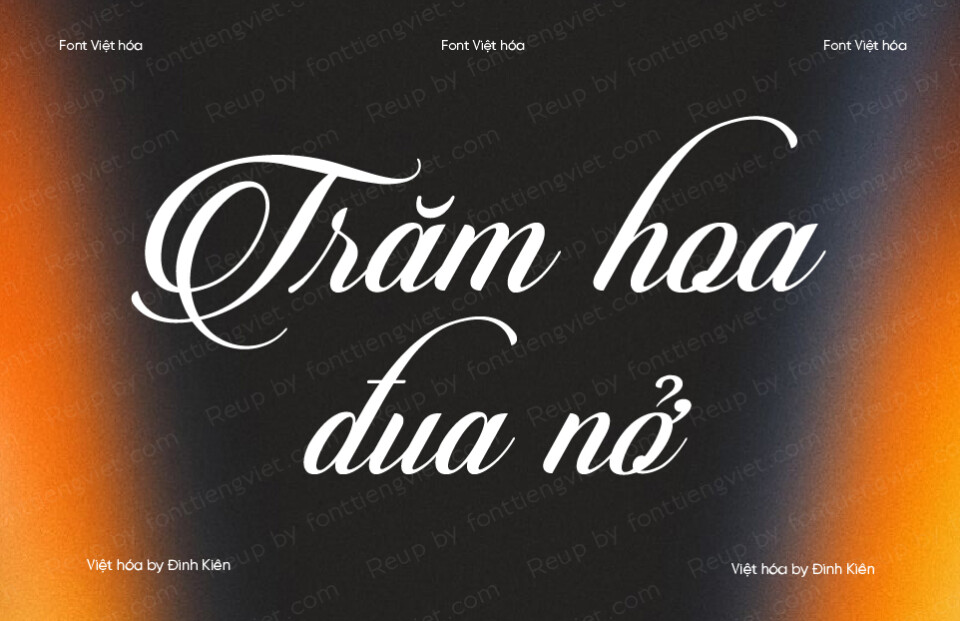
Font Việt hóa UTM Candlescript Pro: Lựa chọn đẳng cấp cho thiết kế thư pháp
Trong thế giới đồ họa hiện đại, việc tìm kiếm một bộ Font Chữ vừa mang nét cổ điển vừa giữ được sự sang trọng là điều vô cùng quan trọng. Font Việt hóa UTM Candlescript Pro chính là giải pháp hoàn hảo dành cho những ai yêu thích phong cách Script bay bổng. Với những đường nét uyển chuyển và hệ thống ký tự thay thế đa dạng, bộ phông này giúp mọi bản thiết kế trở nên sống động và có hồn hơn bao giờ hết.
Đặc điểm nổi bật của Font Việt hóa UTM Candlescript Pro
Sự kết hợp giữa nghệ thuật và công nghệ
Font Việt hóa UTM Candlescript Pro không chỉ đơn thuần là các con chữ mà là một tác phẩm nghệ thuật. Bộ phông được tối ưu hóa với các đường nét thanh đậm rõ rệt, mô phỏng hoàn hảo kỹ thuật viết tay bằng bút lông. Điều này giúp các nhà thiết kế dễ dàng tạo ra các ấn phẩm như thiệp cưới, logo thương hiệu cao cấp hay các bìa sách mang tính nghệ thuật cao mà không tốn quá nhiều công sức chỉnh sửa thủ công.
Tính ứng dụng cao trong học đường và thiết kế
Nhờ đã được Việt hóa chỉn chu, người dùng có thể gõ tiếng Việt có dấu một cách mượt mà mà không lo lỗi hiển thị. Trong môi trường học đường, các em học sinh và giáo viên có thể sử dụng phông chữ này để trang trí báo tường, làm slide thuyết trình hoặc thiết kế các chứng nhận khen thưởng. Sự mềm mại của nó giúp nội dung truyền tải trở nên gần gũi nhưng vẫn giữ được sự trang trọng cần thiết.
Cách sử dụng Font Việt hóa UTM Candlescript Pro hiệu quả
Để phát huy tối đa vẻ đẹp của phông chữ này, bạn nên kết hợp nó với các phông chữ không chân (Sans-serif) đơn giản để tạo sự cân bằng. Việc sử dụng quá nhiều chữ uốn lượn trong một văn bản dài có thể gây rối mắt, vì vậy hãy dùng nó cho các tiêu đề chính hoặc các câu trích dẫn quan trọng. Hãy tải ngay Font Miễn Phí, Font Việt Hóa, Font Việt hóa UTM Candlescript Pro để bắt đầu sáng tạo những sản phẩm độc đáo cho riêng mình ngay hôm nay.